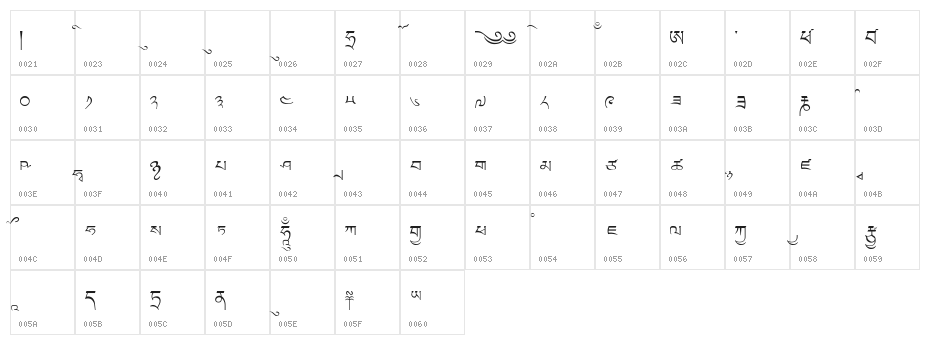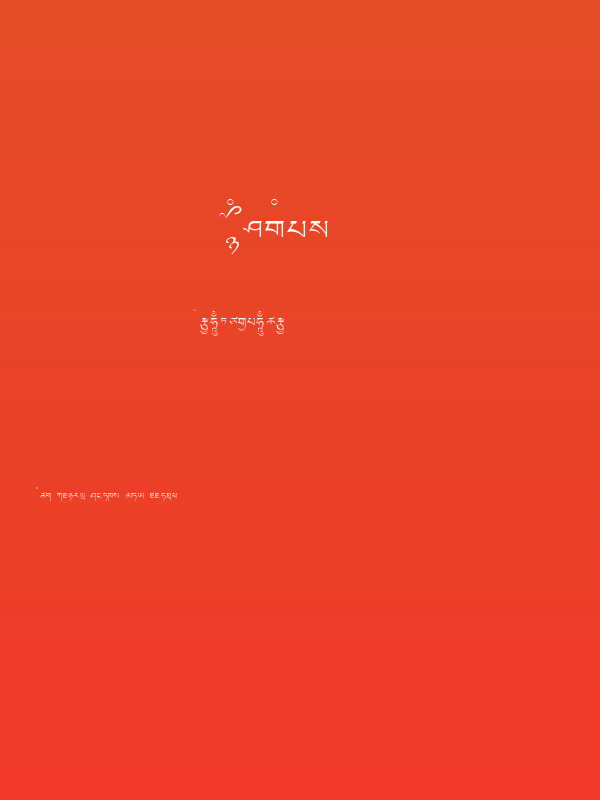
LTibetan Font
| Stile generale | Traditional |
| Caso d'uso | Cultural texts, Religious documents, Artistic designs |
| Progetti proposti | Ideal for cultural and religious publications, educational materials on Tibetan language, and artistic projects that require an authentic Tibetan aesthetic. |